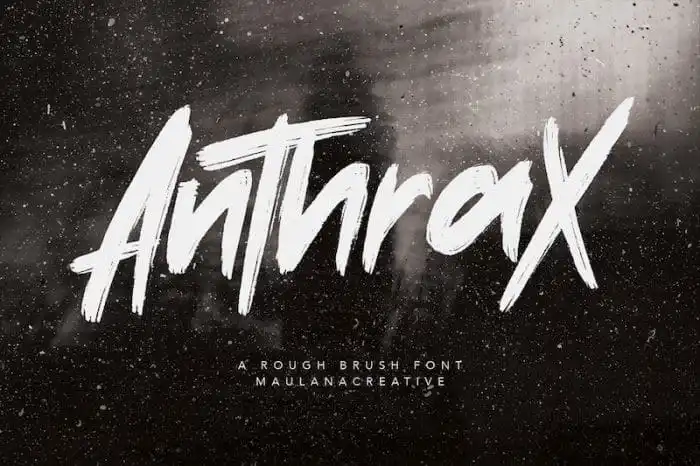
Anthrax Handwritten Font – Download Grátis
Anthrax Handwritten Font é uma fonte script criada com estilo de desenho a mão e canetinha. Ela traz uma atmosfera envolventemente elegante, luxuosa e moderna para qualquer projeto de texto que ela decorará. Seja em um site ou na capa de um livro, essa fonte transformaria seu design de modo único e sofisticado. Para designers e criativos que desejam adicionar um toque especial aos seus projetos, Anthrax Handwritten Font é uma escolha irresistível. Com sua caligrafia única e personalizada, você pode criar texturas que remetem à arte manual, dando ao seu design o brilho de qualidade que ele merece. Em qualquer aplicação para a web ou impressão, essa fonte vai fazer seu texto ser notável, tornando-se um elemento dominante em sua composição visual.